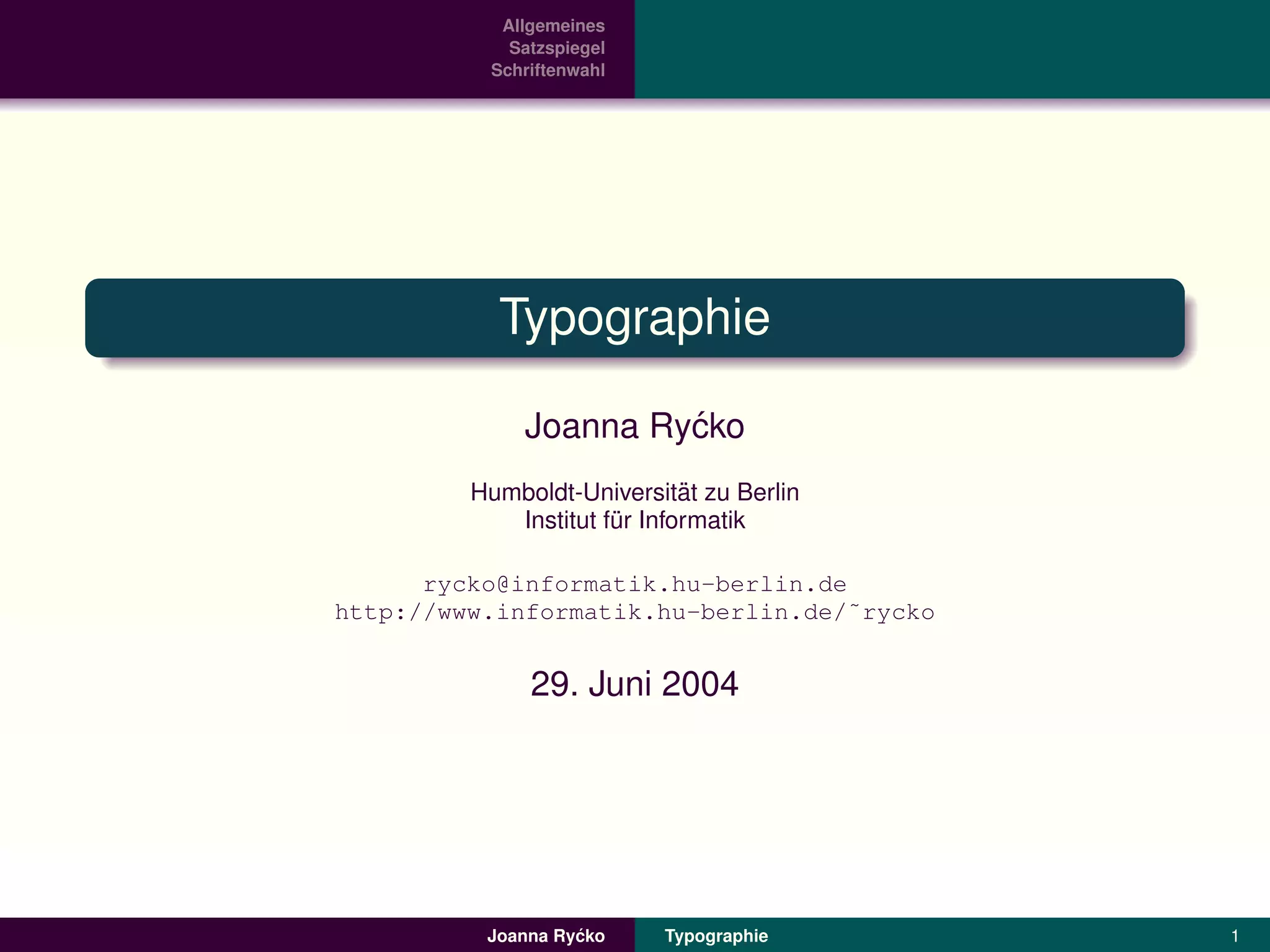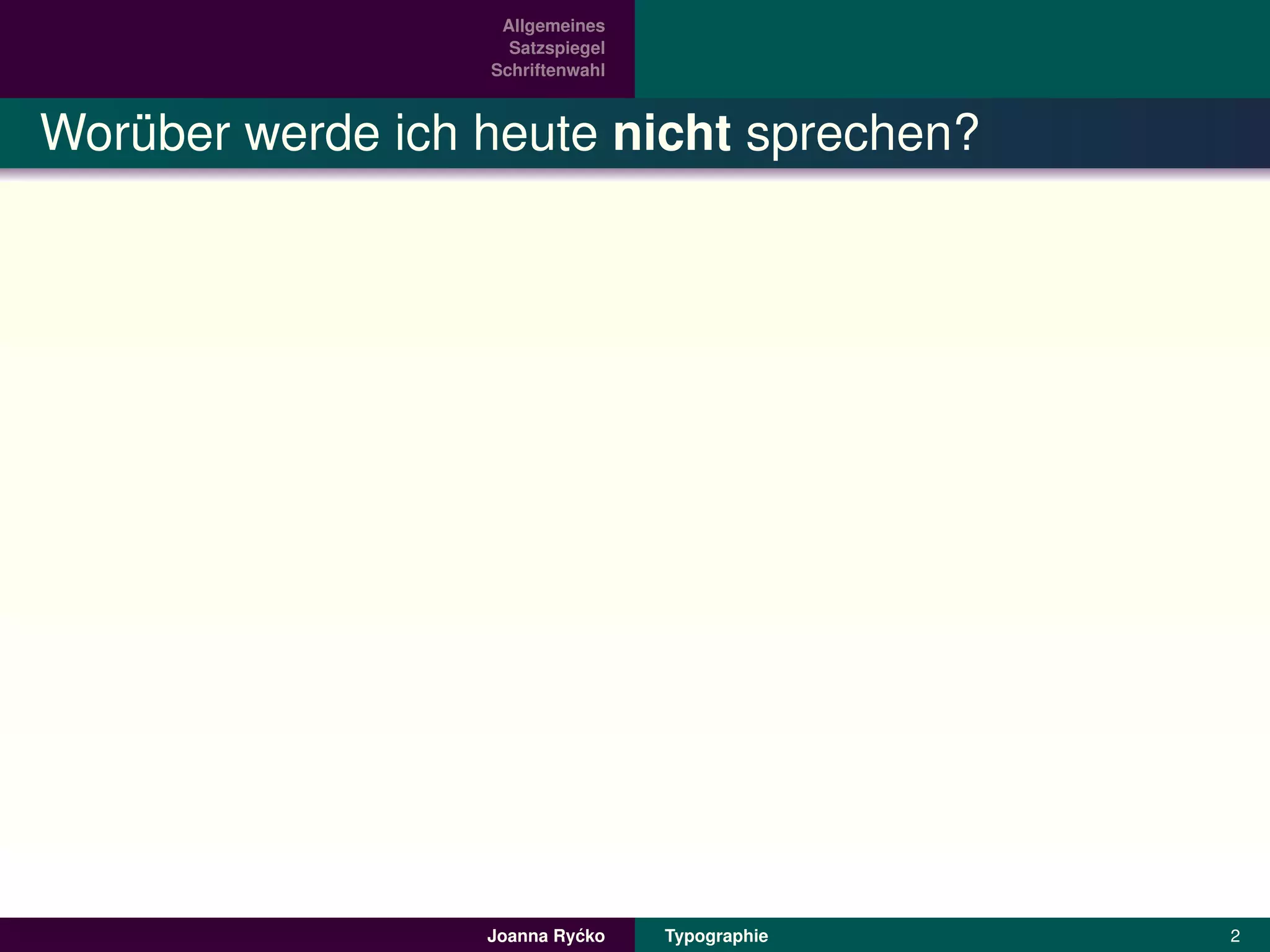
Typographie
Woruber werde ich heute nicht sprechen?
wie man typografische Regeln ins LTEX ubersetzt
aus welchen Teilen ein Buchstabe besteht
was Ligaturen sind
was der Unterschied zwischen -“ –“ und —“ ist
und wann/wie man diese Zeichen verwendet
weil es dafur leider zu wenig Zeit gibt. . . :(
Ich werde aber erklaren. . .
1   Allgemeines
Was ist Typographie?
Wozu uberhaupt Typographie?
Wie erreicht man gute Lesbarkeit?
2   Satzspiegel
Was ist das?
Proportionen und Seitenformat
Stege
Gestaltungsraster, Elemente des Satzspiegels
3   Schriftenwahl
Verschiedene Attributen
Serife
Schriftgroße
Was ist Typographie?
Wozu uberhaupt Typographie?
Wie erreicht man gute Lesbarkeit?
Was ist Typographie?
aus dem Griechischen:
t´pos – Bild, Form
gr´phein – Schreiben
aus dem Griechischen:
t´pos – Bild, Form
gr´phein – Schreiben
heißt also eigentlich:
Schreiben mit Hilfe (vorgepr¨gter) Formen
Typographie – Lehre von:
den einzelnen Buchstaben
der Zusammenfugung einzelner Buchstaben
der Zusammenfugung von Buchstaben zu Wortern
und weiteren gliedernden Elementen
Wozu uberhaupt Typographie?
Asthetik
Lesbarkeit